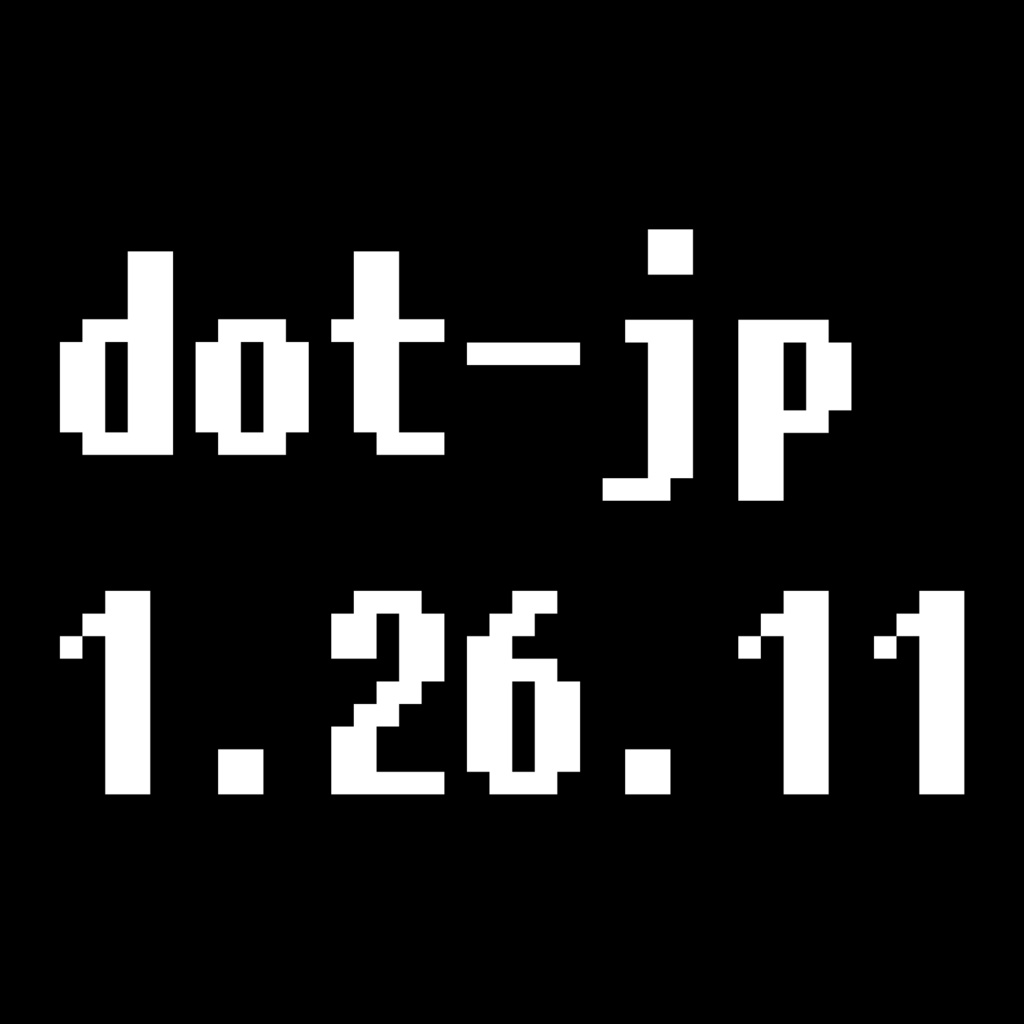
創リノ舗【無料】"マイクラっぽい"フォントにしよう!「dot-jp」【マインクラフト統合版アドオン】】無料版Digital0 JPY무료 다운로드dot-jp_v1.0.0.zip (242KB)dot-jp_v1.0.0.zip支援版(中身同一)Digital300 JPY카트에 담기기프트 보내기About Giftこのアドオンをグローバルリソースに入れ、言語設定を「English (United States)」にすると、Java版のようなドットの"マイクラっぽい"日本語フォントでマイクラをプレイすることができるようになります。 また、ローカルファイルとしてワールドに設定することで、SwitchやPS4のユーザーにも適用可能です。 ※ワールド生成の画面には残念ながら対応させることができませんでした。ご了承ください。創リノ舗Visit FANBOX!Acrylic Keychains【創リノ輪】miniアクリルキーホルダー お茶緑創リノ舗900 JPYAcrylic Keychains【創リノ輪】miniアクリルキーホルダー いちごあめ創リノ舗900 JPYAcrylic Keychains【創リノ輪】miniアクリルキーホルダー まっつん創リノ舗900 JPYAcrylic Keychains【創リノ輪】miniアクリルキーホルダー R.P創リノ舗900 JPYAcrylic Keychains【創リノ輪】miniアクリルキーホルダー 黒糖クロワッサン創リノ舗900 JPYAcrylic Keychains【創リノ輪】miniアクリルキーホルダー えるぜん創リノ舗900 JPYGame-related Items【マイクラ統合版アドオン】太陽vs人間!?全てを破壊する太陽から逃げ切れ!【遊び大社】創リノ舗0 JPYGame-related Items【無料】松明を持ってあたりを照らす「Offhand Torch Addon」【マインクラフト統合版1.26.10】創リノ舗300 JPYSoftware【無料】ElectronHelper【1.0.0】創リノ舗500 JPYGame-related Items【無料】【マイクラ】統合版でも透明額縁を使いたい!創リノ舗350 JPYGame-related Items【無料】【マイクラ】”本当の”透明化を実現!創リノ舗350 JPYGame-related Items【無料】他人の視点を見てみよう!「View Command Addon」創リノ舗350 JPYGame-related Items【無料】マイクラの時間を現実時間と同期!「Time Set from Real Addon」創リノ舗350 JPYGame-related Items【無料】マイクラ統合版対応 スキンチェンジャー v1.0創リノ舗350 JPY더보기